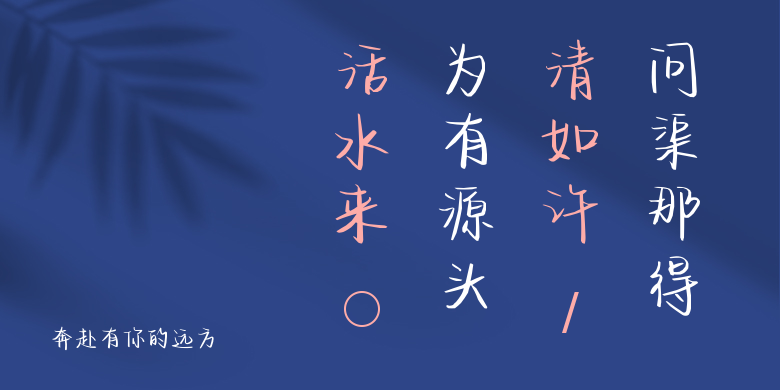
奔赴有你的远方
奔赴有你的远方,这款字体结构工整、笔画清晰,兼顾美观与易读性,适用于标题、正文、海报、包装、LOGO 等多种场景。字形优雅稳定,风格百搭耐看,适配日常排版与创意设计,让文字呈现更舒适、更具质感。奔赴有你的远方一笔一画,皆是细节,以均衡的比例、流畅的线条打造舒适视觉体验,字形端正大气,风格简约现代。无论是商业设计、品牌宣传还是日常排版,都能轻松驾驭,让文字更有格调与力量。奔赴有你的远方字体下载。